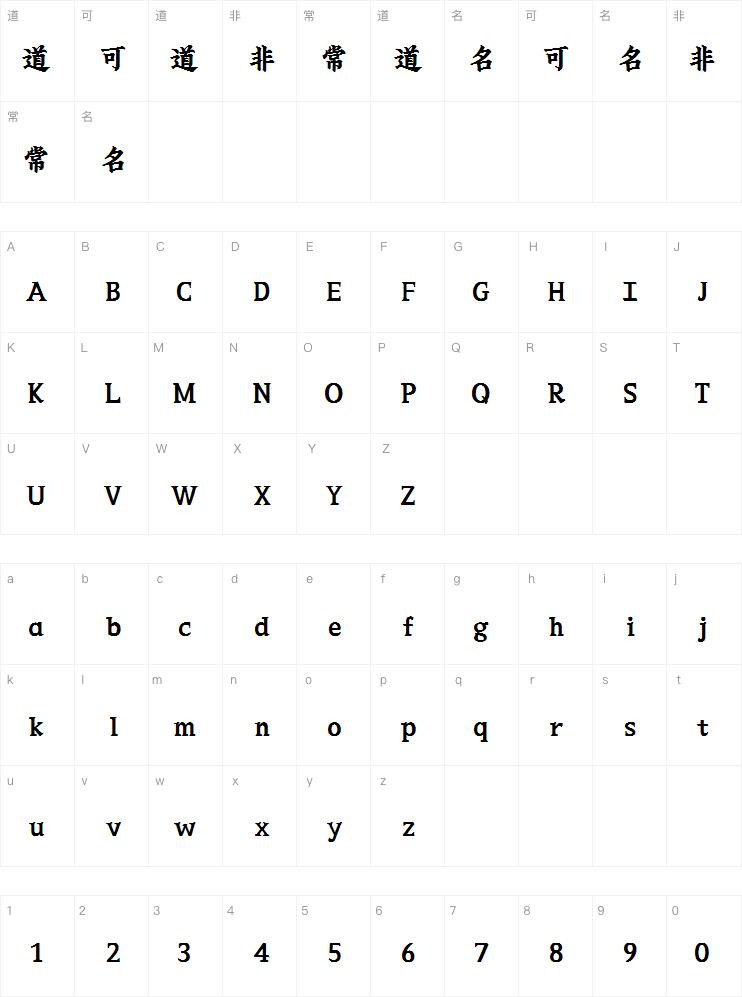
山海聚珍刻宋95W,是一款全新的字体,是山海山海聚珍刻宋字体家族系列中的特粗款,编号95W,包含汉字9169个,符号200+个。该字体是一款国风复古刻本字体,字形秉承中国宋代古籍善本之字形特性,宋刻本是中国古籍中最为珍贵的版本之一,素有“一页宋版,一两黄金”的说法,被历代藏书家、学者奉为瑰宝,该字体秉承了宋代刻本版刻刀法剔透,字形方正,端庄严谨,古朴大方,起落顿笔有棱角的特点。该字体采用柳体(柳公权)为基础蓝本,在饱有笔墨之意、秀劲有力的同时,又突显刀刻之锋美,笔刀结合刚柔并济,带有浓厚的书法韵味,笔画顿挫有力,结构严谨,看上去赏心悦目。在秉承笔形间创新,结合当代设计视觉环境,融入现代审美,适用场景更多元,笔画造型清晰锐利,删繁取简,笔锋凌厉,速度感强,粗细对比强烈,完美地再现宋刻本字体的秀美。转折、顿挫、波磔(捺笔)等书法细节都雕刻得淋漓尽致,使其完美重现刀刻宋刻本古韵之美。